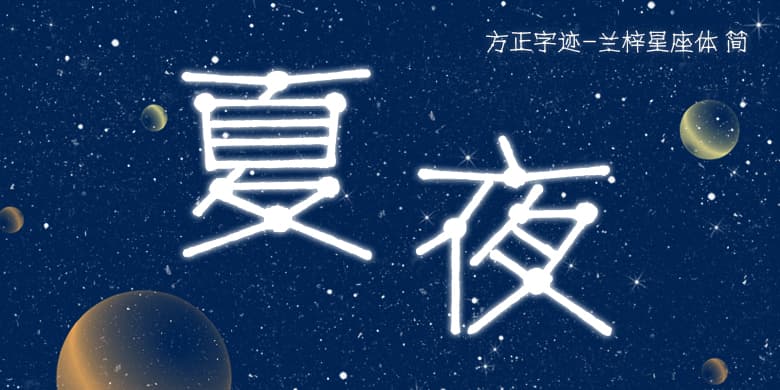
方正字迹-兰梓星座体
品牌:方正字迹设计师:张惟梓发行时间:2021字库编码:大陆简体(GB2312-80)分类:创意书写字体属性:精品字
仰望星空,你所能见到的最美的是什么?每当看到繁星点点,那有着不同美丽传说的星座,就会在脑海浮现。兰梓星座体,正是来源于这种灵感,将一颗颗璀璨的星星,用线条连成像星座一样的汉字,字体空灵浩瀚,斗转星移,穿越苍穹,在宇宙的尽头化作一个个最美丽的符号。
作者张惟梓,男,1956年出生于山东淄博,本科学历。曾任山东省青年摄影家协会会员、淄博市摄影家协会会员。擅长绘画、摄影及美术字设计等,长期从事企业文化、宣传及产品设计开发工作,摄影及美术作品曾多次参加省市级展览。